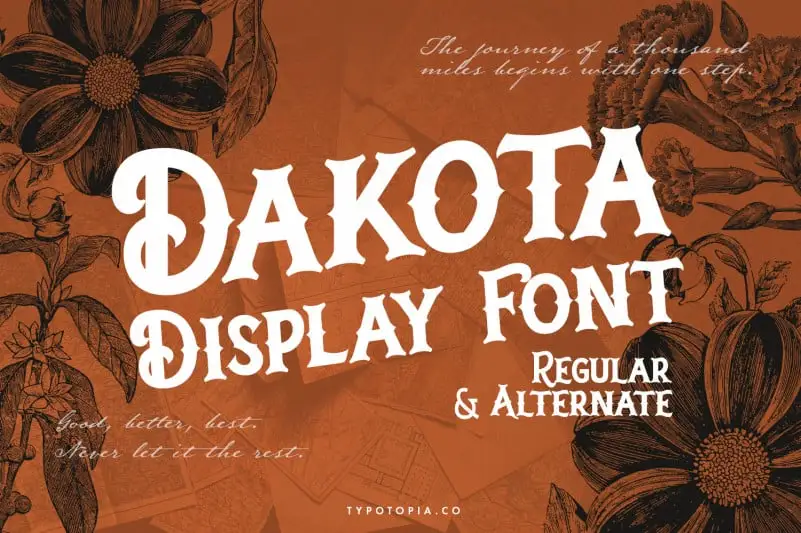
Dakota Display Font – Download Grátis
A Dakota Display Font é uma escolha perfeita para quem busca um equilíbrio entre a nostalgia do passado e a modernidade atual. Inspirada nos belos desenhos antiguidades, essa fonte possui um visual robusto e fresco ao mesmo tempo. É um verdadeiro passeio pela história da tipografia, mas com uma aparência que faz jus à era digital. A Dakota Display Font vem em duas variedades de estilo: Regular e Alternate. Cada combinação foi cuidadosamente refinada para garantir que suas criações saiam ainda melhores. Seja você um designer ou um criador de artesanato, a Dakota Display é uma opção excepcional para quem busca uma fonte vintage que se adapta perfeitamente ao seu projeto moderno.